ダイナフォント2024年秋の新書体では、2024年グッドデザイン賞受賞書体としても今後ますます注目を集める「金蝶体」の新欧文バージョンから人気書体の新かなデザイン書体、テロップ新書体や欧文新書体などを提供。
2024年グッドデザイン賞を受賞した詩情に溢れる“金蝶体”の新欧文バージョン「金蝶体B」
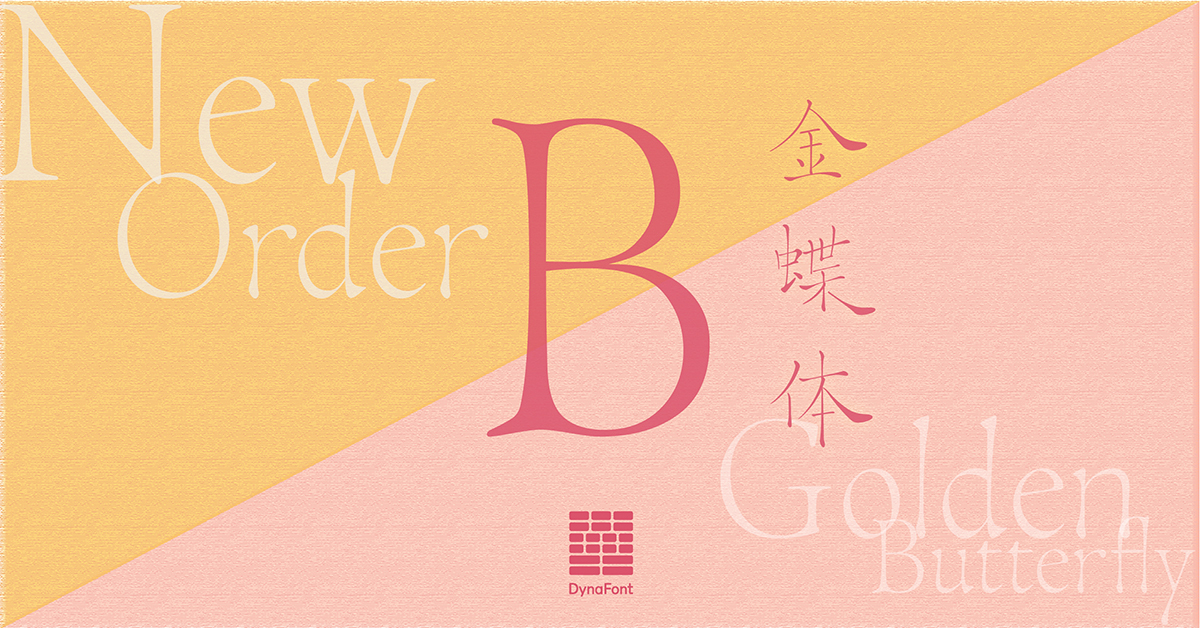
「金蝶体」は台湾の高名な詩人である周夢蝶氏の小楷書道から着想を得て、手書きの慎重さとぬくもりをそのままに“蝶”をコンセプトとして、躍動する生命力を表現したダイナフォント2024年話題の新書体となる。
10月16日に2024年グッドデザイン賞を受賞するなど、リリースから現在に至るまで大きな注目を集める「金蝶体」に、2024年秋の新書体として新デザインの欧文を収録したバージョン「金蝶体B」がリリースされた。
「金蝶体B」では2024年の春に先行リリースした「金蝶体A」と異なる筆の質感にこだわり漢字の雰囲気により近づけた新たな欧文を収録している。
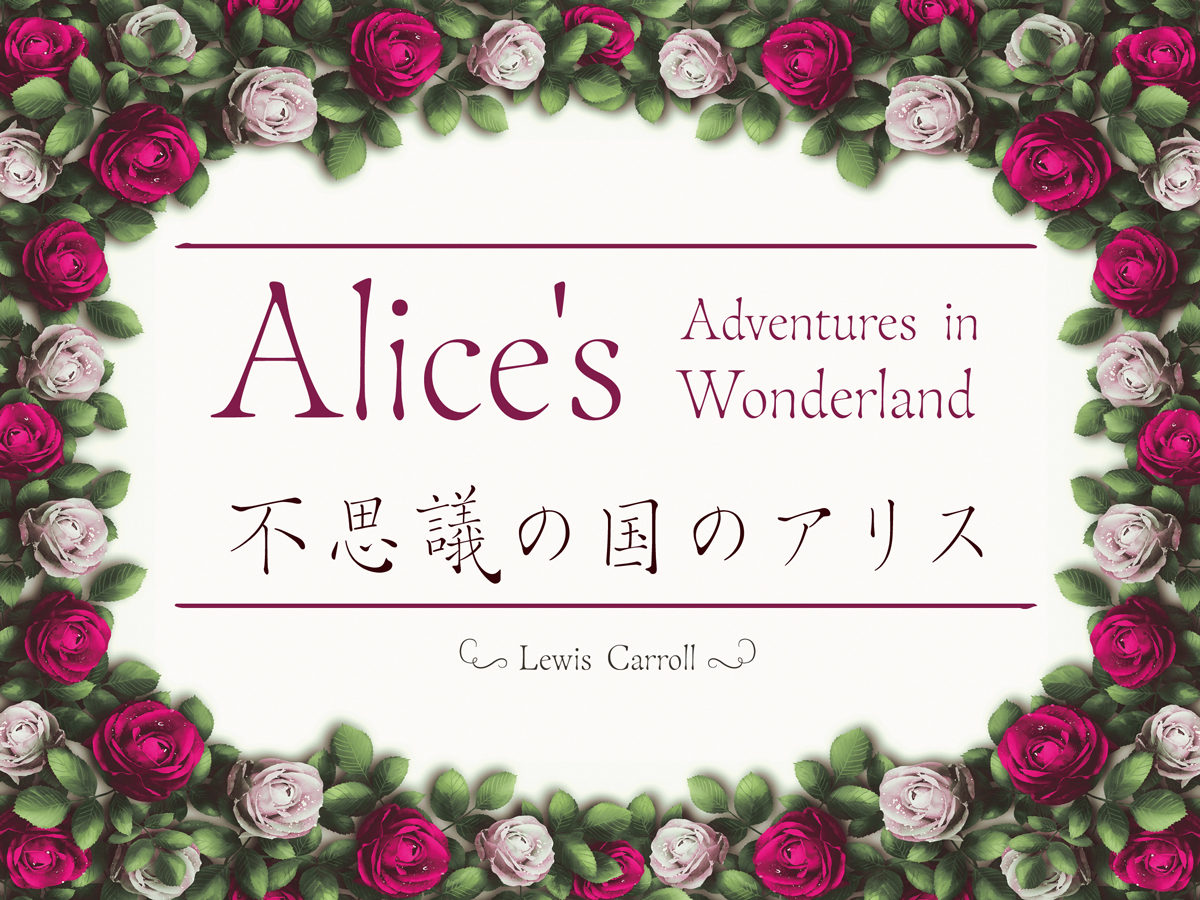
安定感のある“かな”による新たな水袖の文字「京劇体A」
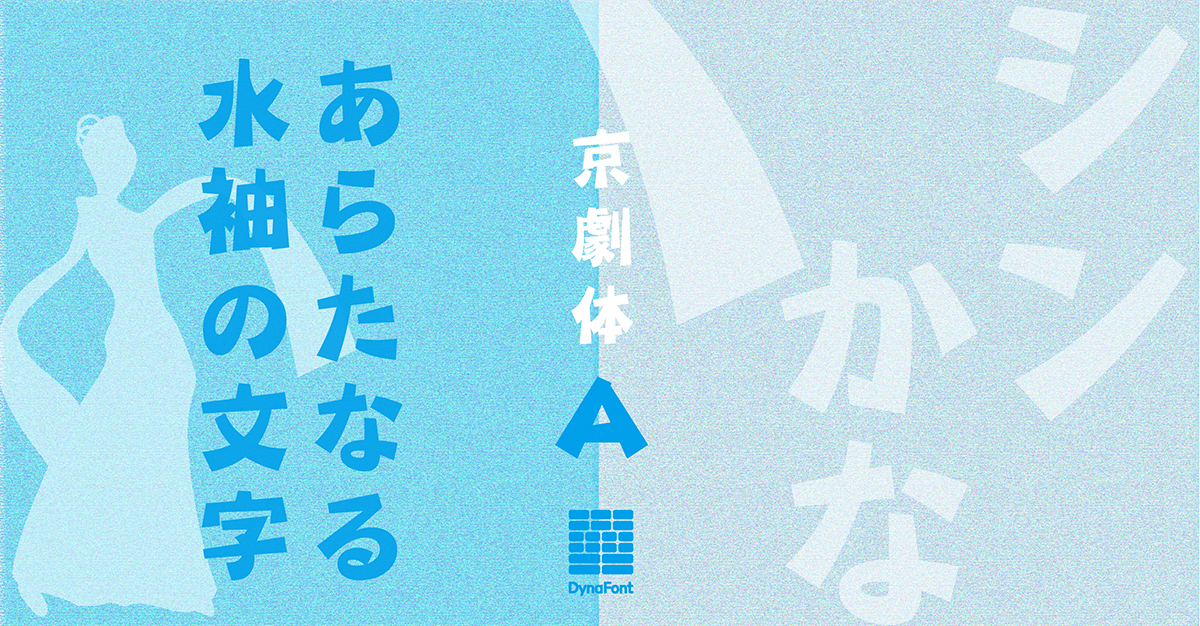
「京劇体」はゴシック体をベースに、中国の伝統演劇である“京劇”で着用する衣装の袖に付けられた“水袖”と呼ばれる白い絹をモチーフにして喜怒哀楽を表現した人気書体。
「京劇体A」では従来の「京劇体」と異なる、安定感のある新たな“かな”を収録している。
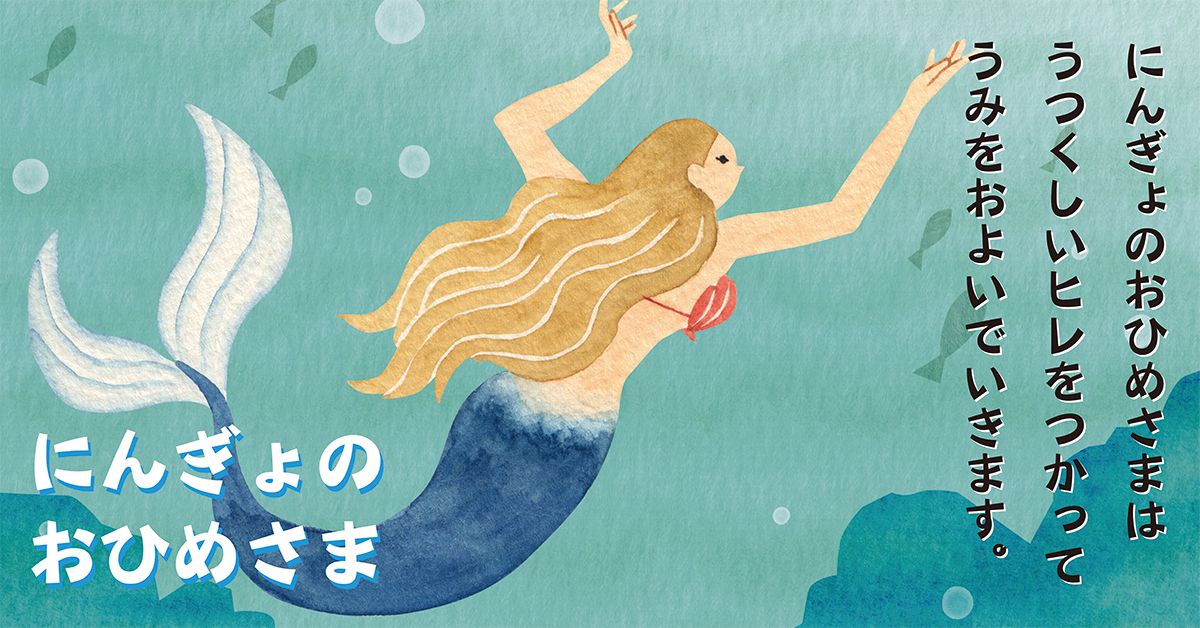
記号的な“かな”による新しいPOPな文字「POPミックスA」
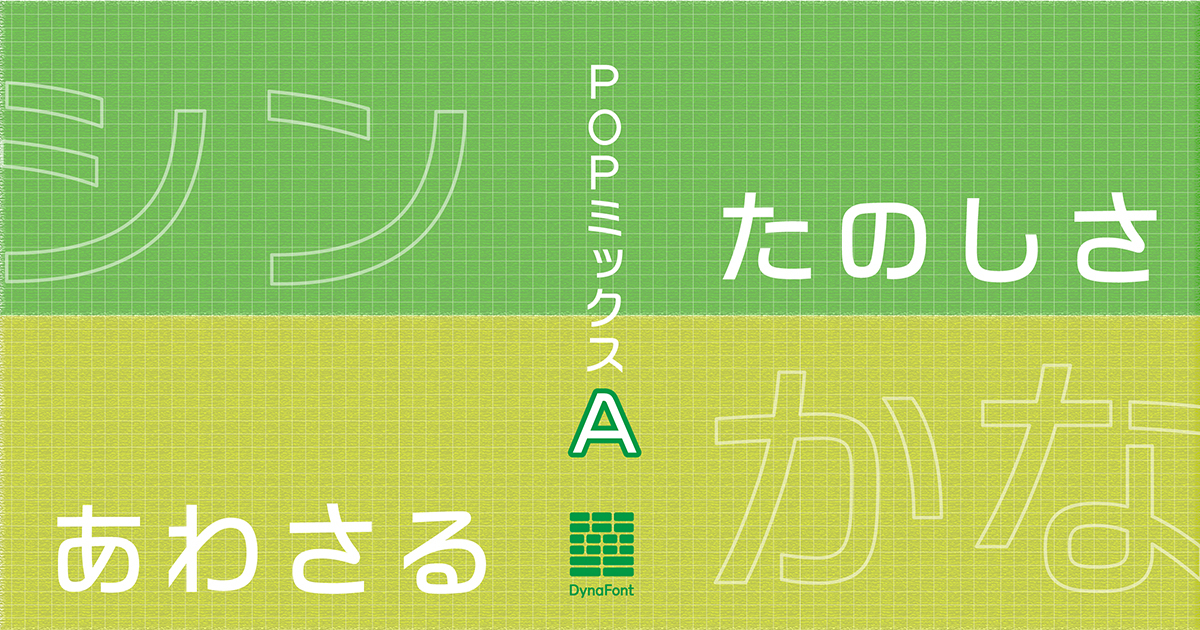
「POPミックス」は均一な線とD形のエレメントが特長となるPOP系書体で、端正な雰囲気の中にも遊び心を持ち合わせ、様々な場面で使用されている人気書体となる。
「POPミックスA」では従来の「POPミックス」と異なる、漢字との統一感を出した新たな“かな”を収録している。
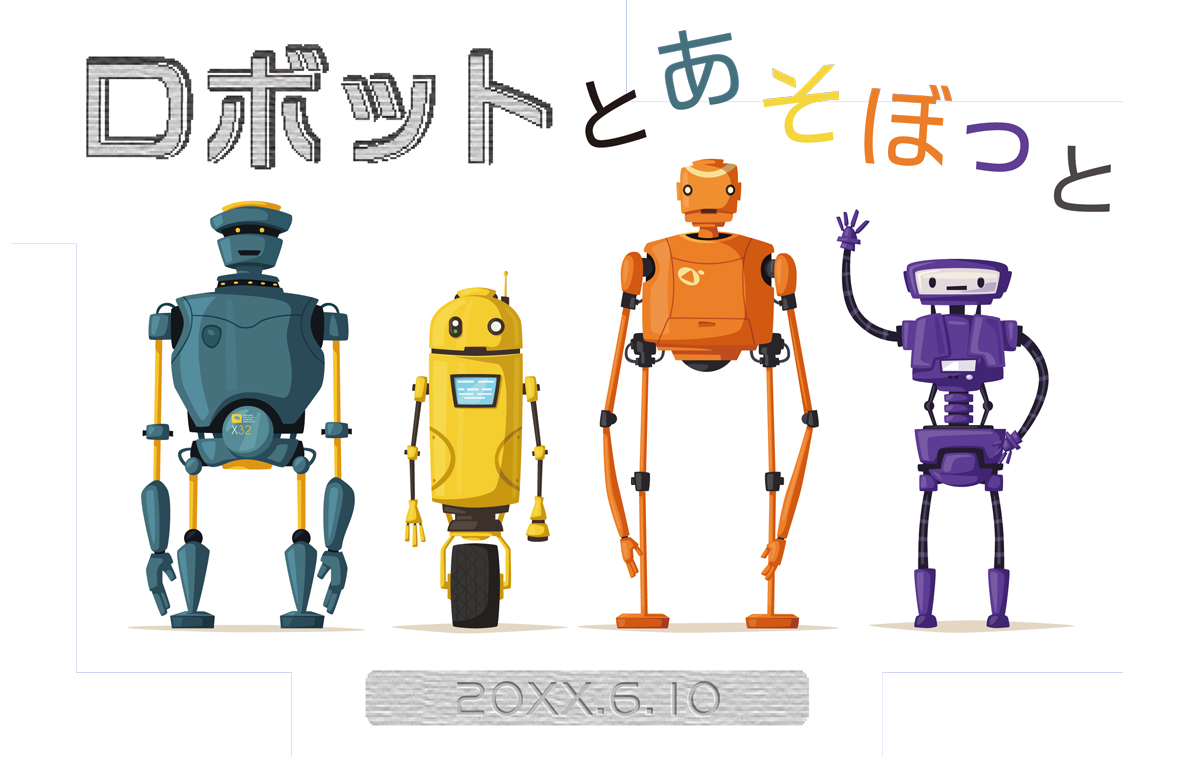
人気デザイン書体“綜藝体”のテロップ書体「綜藝体S」
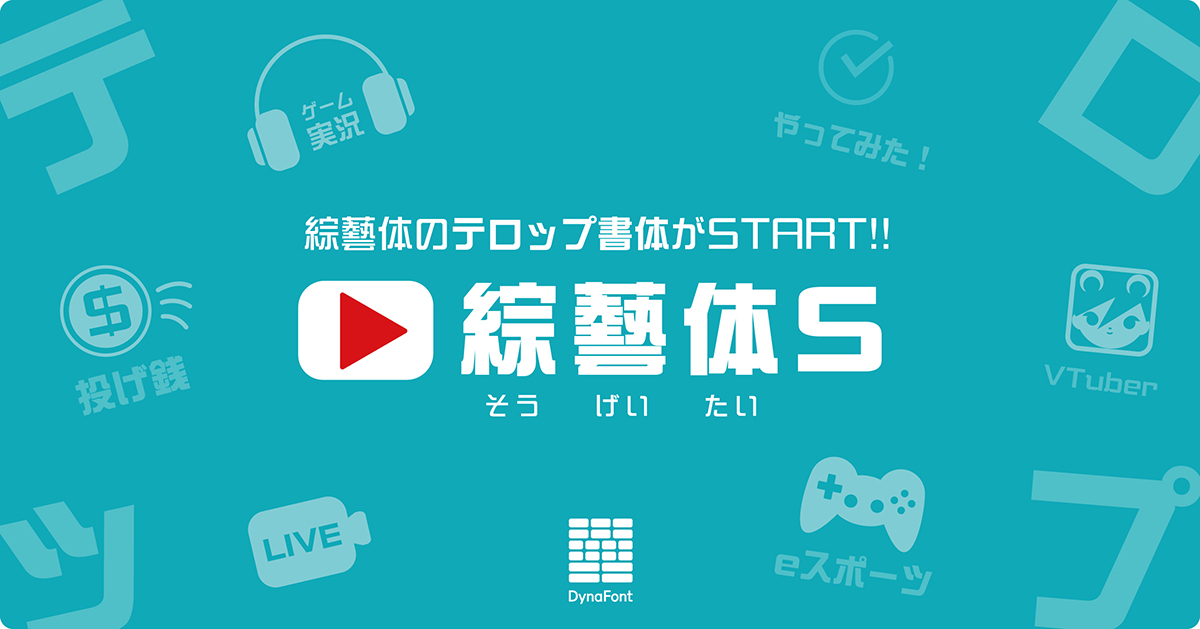
「綜藝体」は、ゴシック体をベースとした正方な形に、曲がりやハネの先端部分をカーブさせたデザイン書体。
インパクトがありながらも軽妙さもある字形は汎用性に優れており、映像やゲーム、コミックなど様々なコンテンツで多くの採用実績がある。
「綜藝体S」は“テロップ書体”として「綜藝体」を液晶画面のあらゆるサイズでの表示に対応させた。
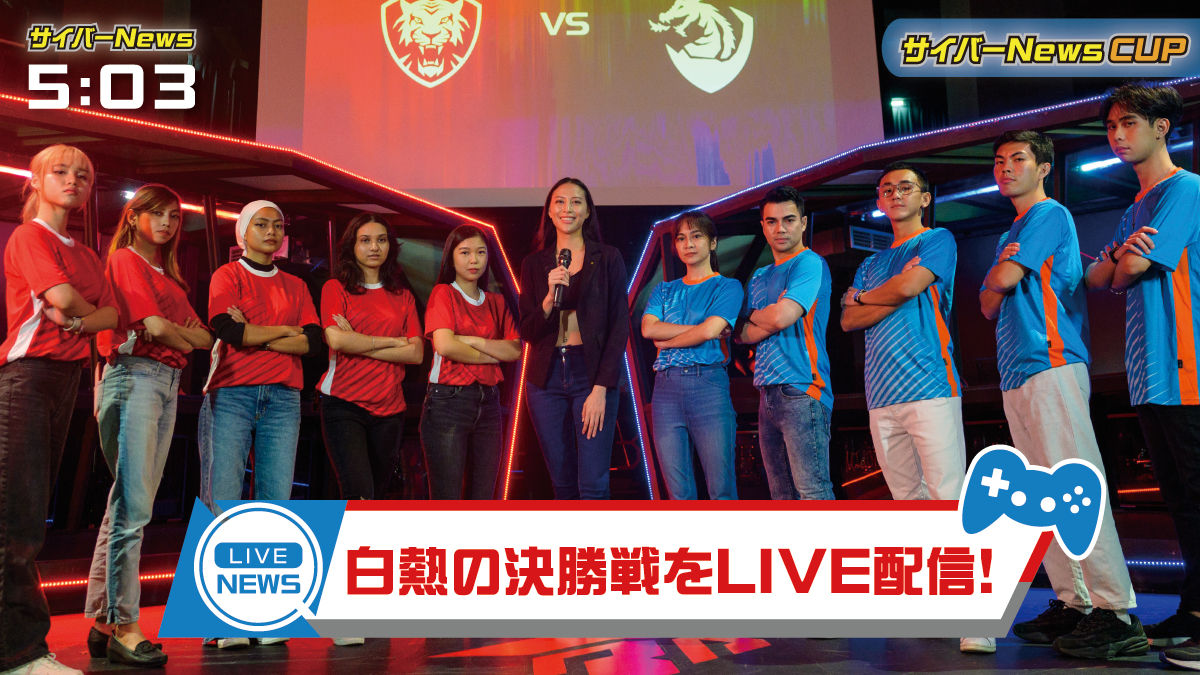
明るくクリーンな韓国語の文字「青花ゴシック体 韓国語」
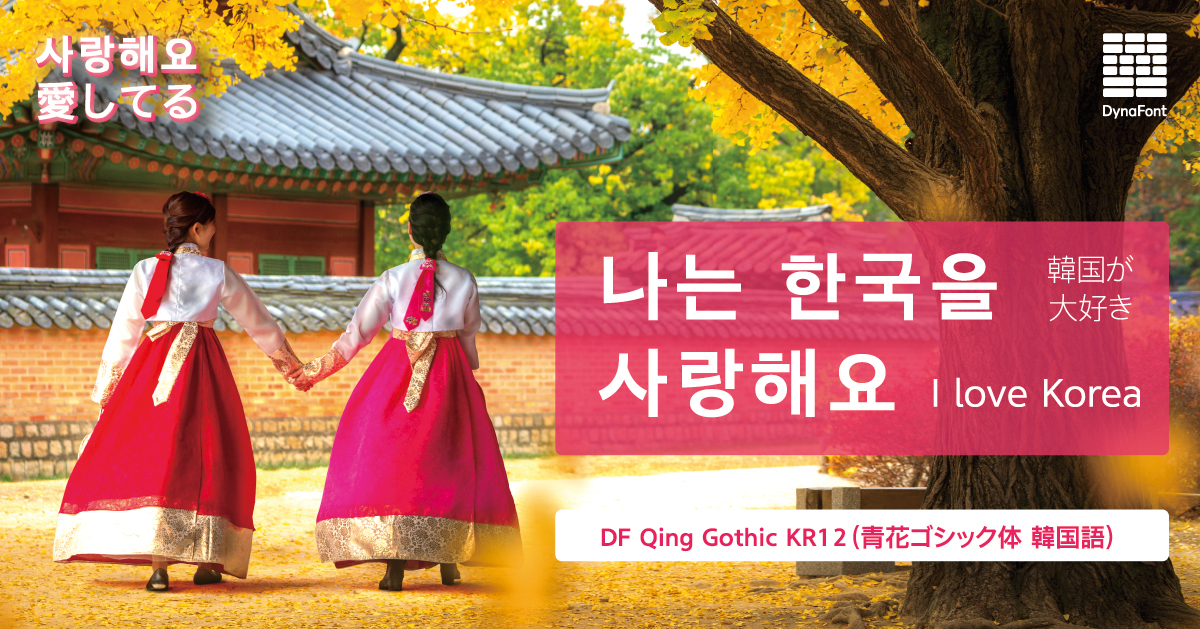
「DF Qing Gothic KR12(青花ゴシック体 韓国語)」は、Webなどのデジタルデザインでの使用を念頭に、明るくクリーンなイメージに仕上げたニュートラルなゴシック体による韓国語フォント。
先行リリースした日本語版同様、シンプルでモダンな字形に広々としたふところ、字幅によって筆画間の空間を狭めることで向上した視認性と柔らかい読み心地が特長となる。
W1~W7まで7ウエイト、文字セットはAdobe-Korea1-2準拠による18,352文字に対応している。
柔剛競演によるタイ語の文字「金剛明朝体 タイ語モダンタイプ」
「DF King Serif THM10(金剛明朝体 タイ語モダンタイプ)」は、彫刻の鋭敏さを和らげて書の人間味あふれる気品を備えることで視覚的にも温かくやさしい印象を与える「金剛明朝体」の特長を受け継いだタイ語のモダンタイプのフォント。
モダンタイプはループがないデザインなど欧文との親和性が高く、先行リリースしているループがある伝統的なスタイルの「金剛明朝体 タイ語」と用途に合わせて使い分けることが可能になった。
W2~W9まで8ウエイト、文字セットはUnicode準拠による211文字に対応している。
使って楽しい個性豊かな5種類の欧文フォント
ダイナフォント「JoyfulPen(ハンジペン)」
ダイナフォント「NotePen(ハンノテート)」
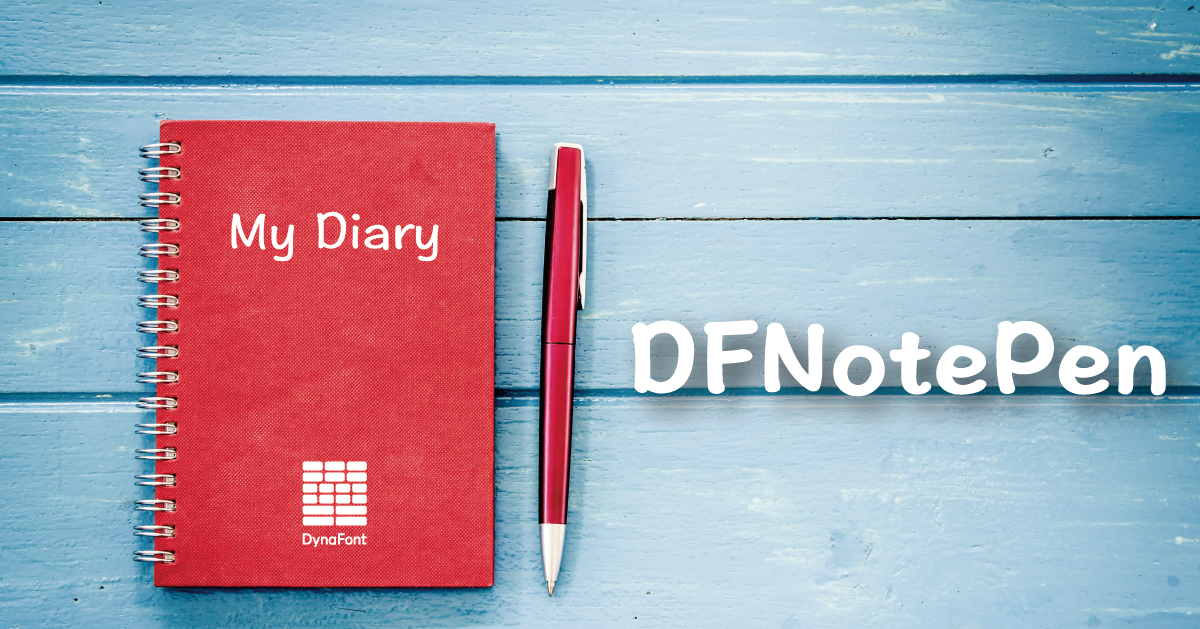
ダイナフォント「TechnoGrid(綜藝体)」
ダイナフォント「GirlyPen(まるもじ体)」
ダイナフォント「TimelessSerif(玉刻華宋)」
ダイナフォントの強いデザイン性を活かした5種類の欧文フォントの提供を開始した。
・DFJoyfulPen(ハンジペン)
・DFNotePen(ハンノテート)
・DFTechnoGrid(綜藝体)
・DFGirlyPen(まるもじ体)
・DFTimelessSerif(玉刻華宋)
文字セットはUnicode準拠による235文字に対応している。
宋朝体をデジタル表示用に磨き上げた“千磨百錬”の文字「玉刻華宋」
「玉刻華宋」は中華民国初期の宋朝体から実際に印刷された書体見本を参考に、デジタル表示用として丹念に磨き上げた書体。
明朝体と楷書体のエレメントを兼ね備えた縦長の字形に力強く鋭い画線が特長で、かなには「津田三省堂」のタイトルとして使われている宋朝体のかな活字をベースに漢字の要素も取り入れた。